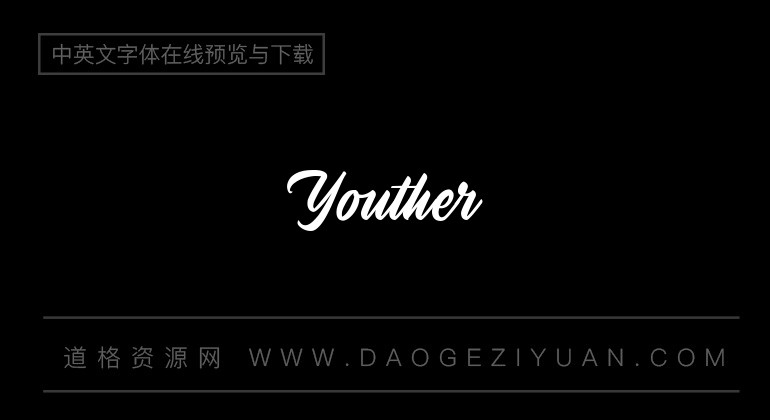
Youther 字体是一款具有现代感的多功能字体,具有精致的曲线细节,可以帮助您轻松创作出精美的文本和标题设计。它可以用于任何类型的设计,包括海报,书籍,网页,品牌标识,印刷材料等等。它可以帮助您轻松创作出精美的设计,提供您更多的创意空间。 Youther 字体还支持多种语言,可以完美地显示您的文本,让您的设计更加出色。内容介绍
Youther是一款非常不错的手写艺术字体,具有很好的视觉感,适合于文化类的宣传设计、商业类品牌的广告和产品包装设计以及个性化文字排版等较多场景。